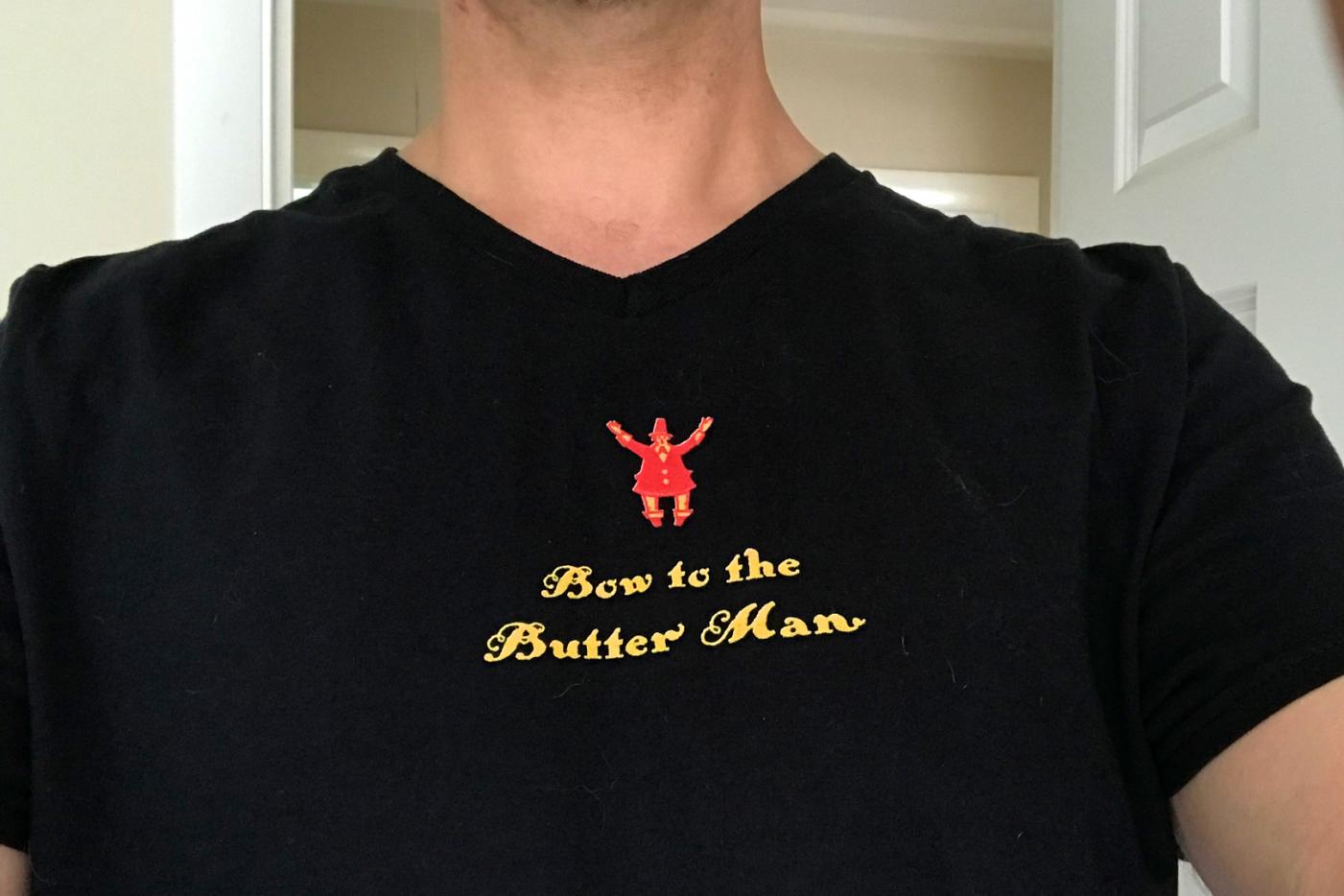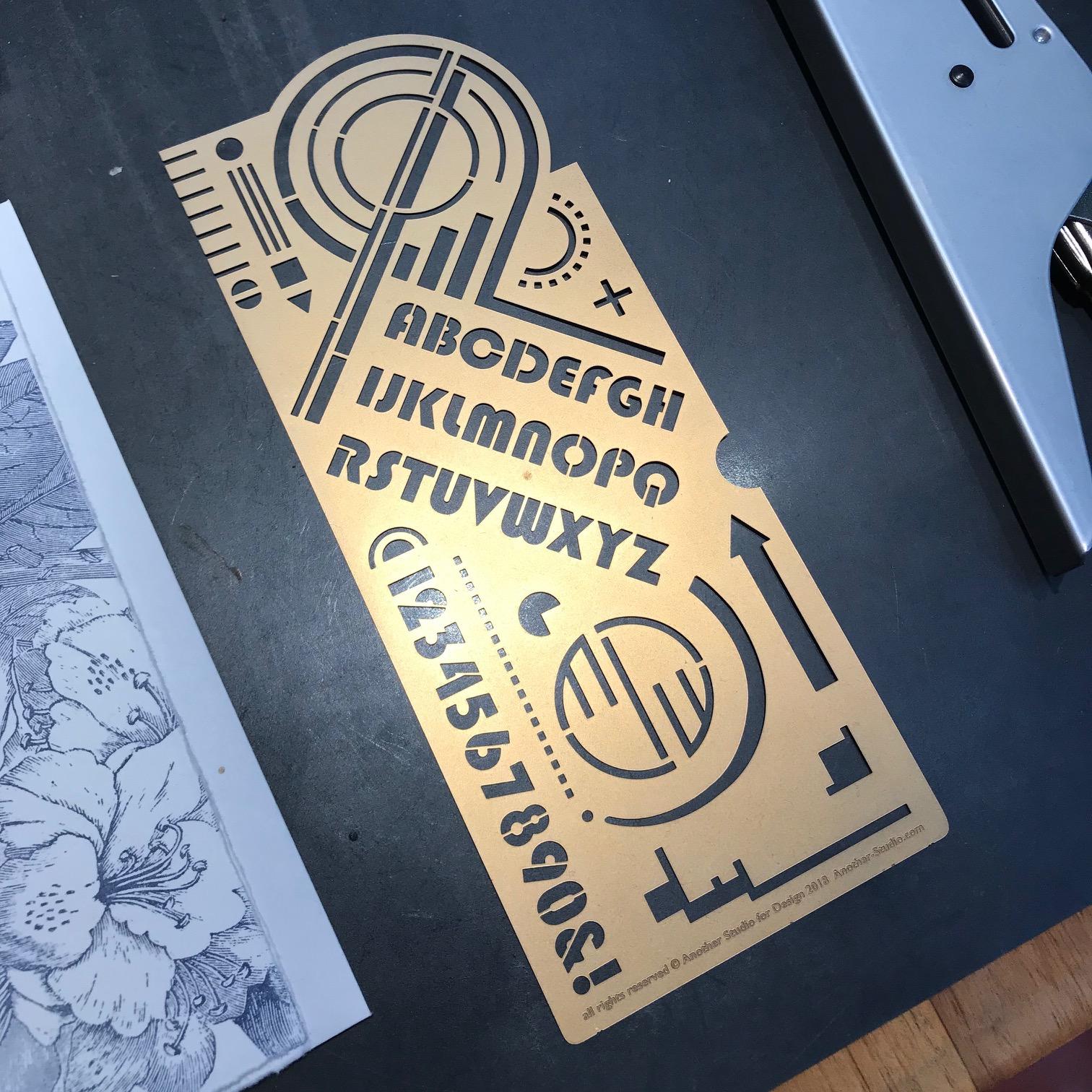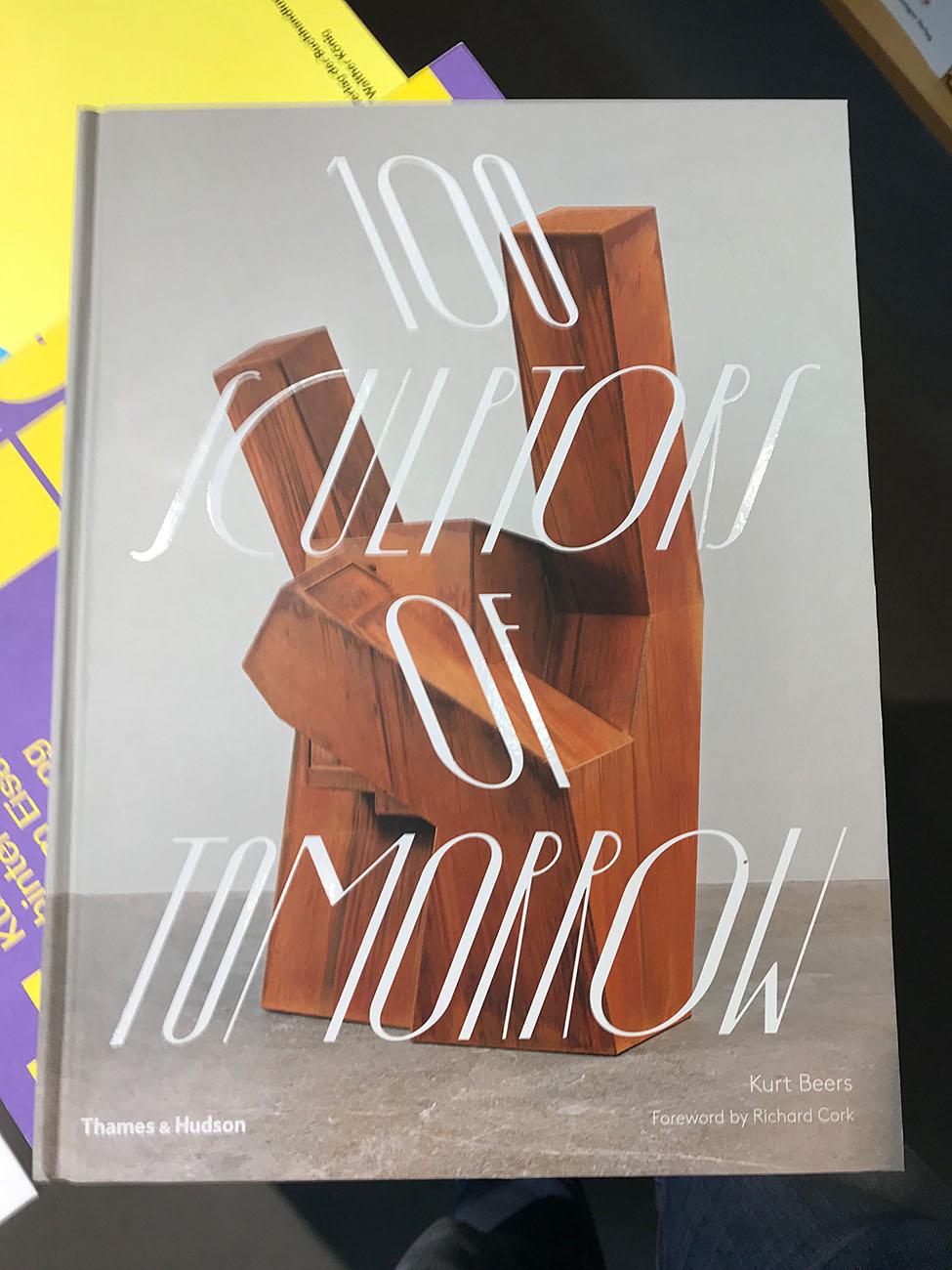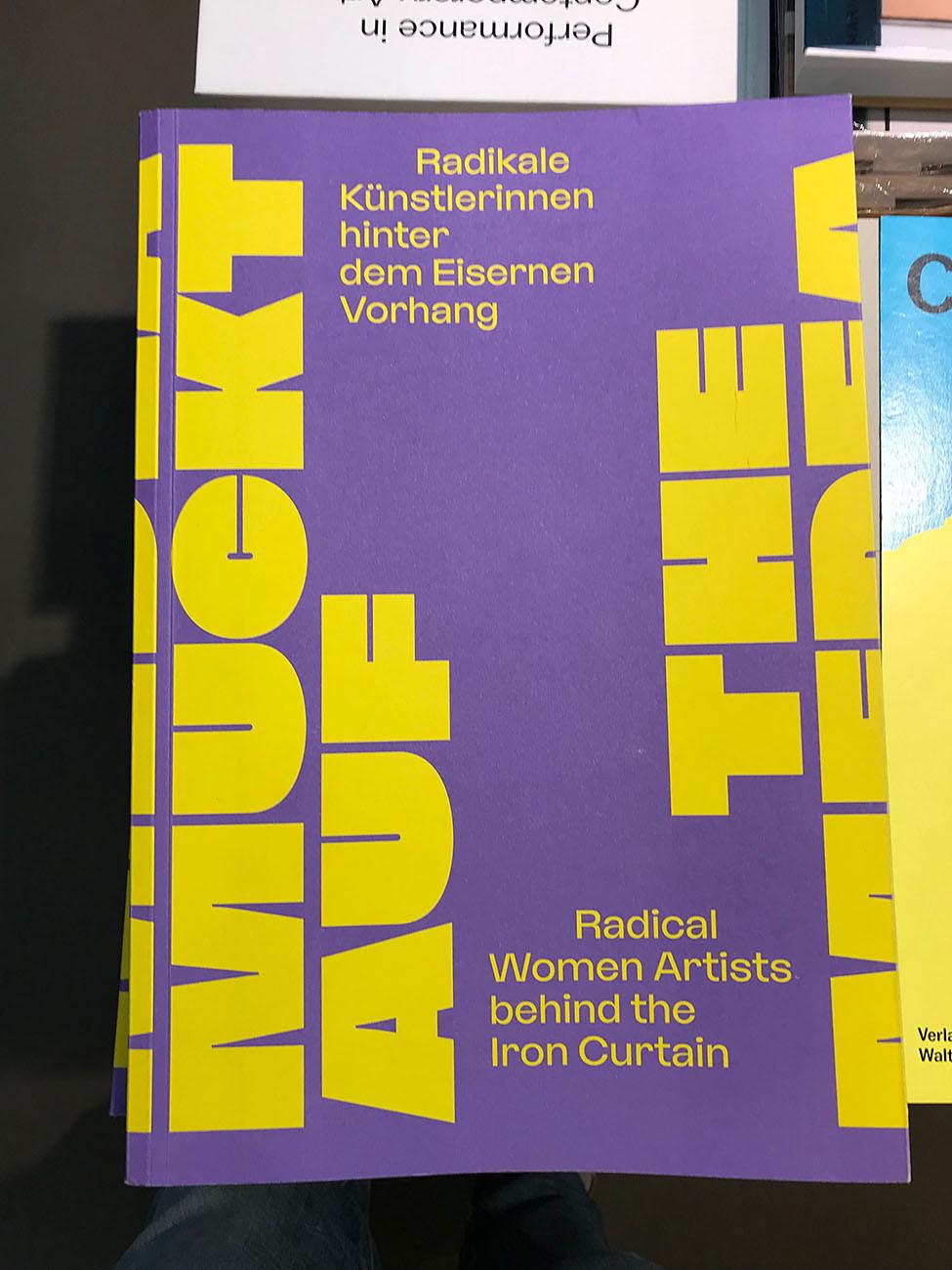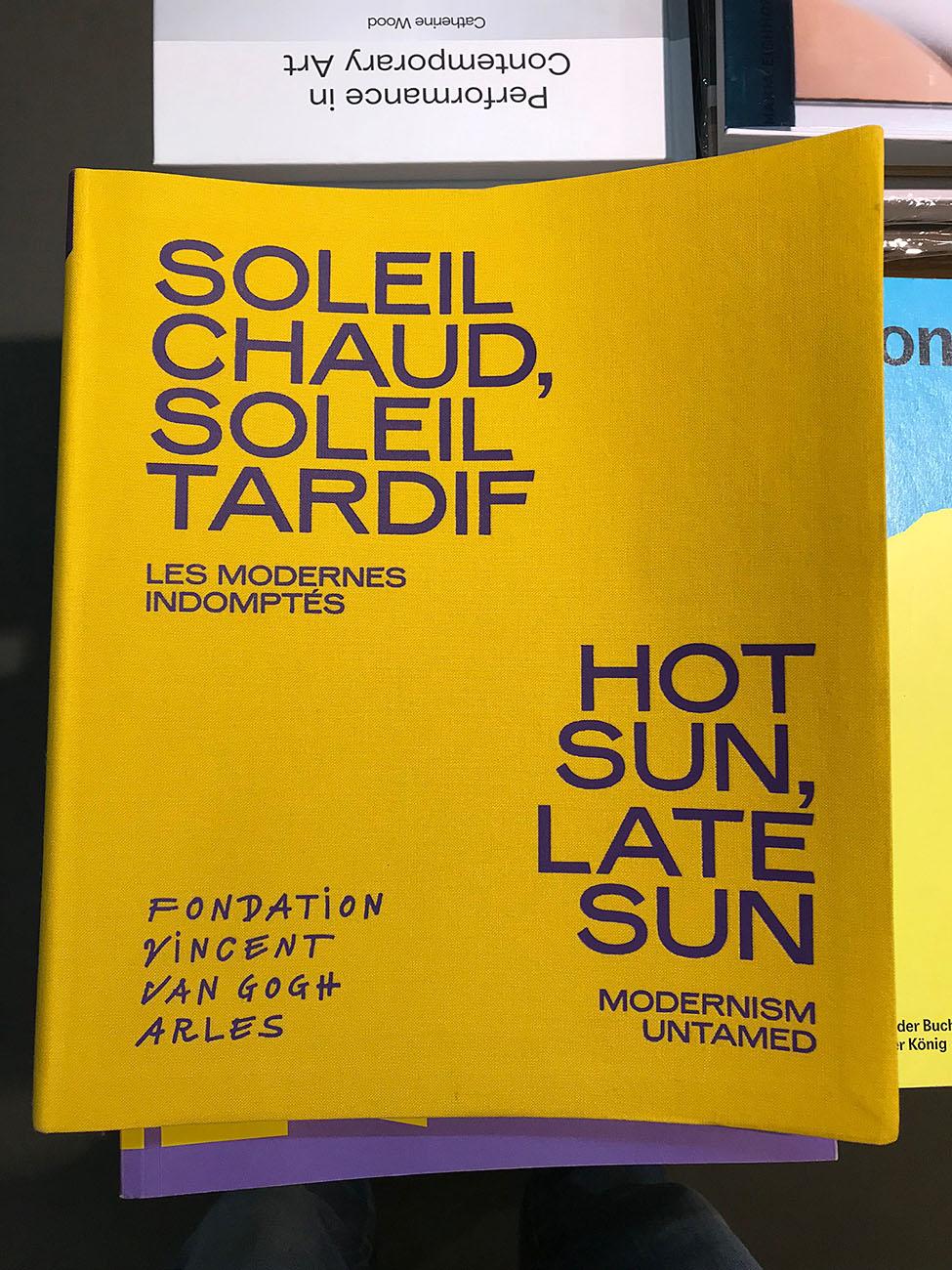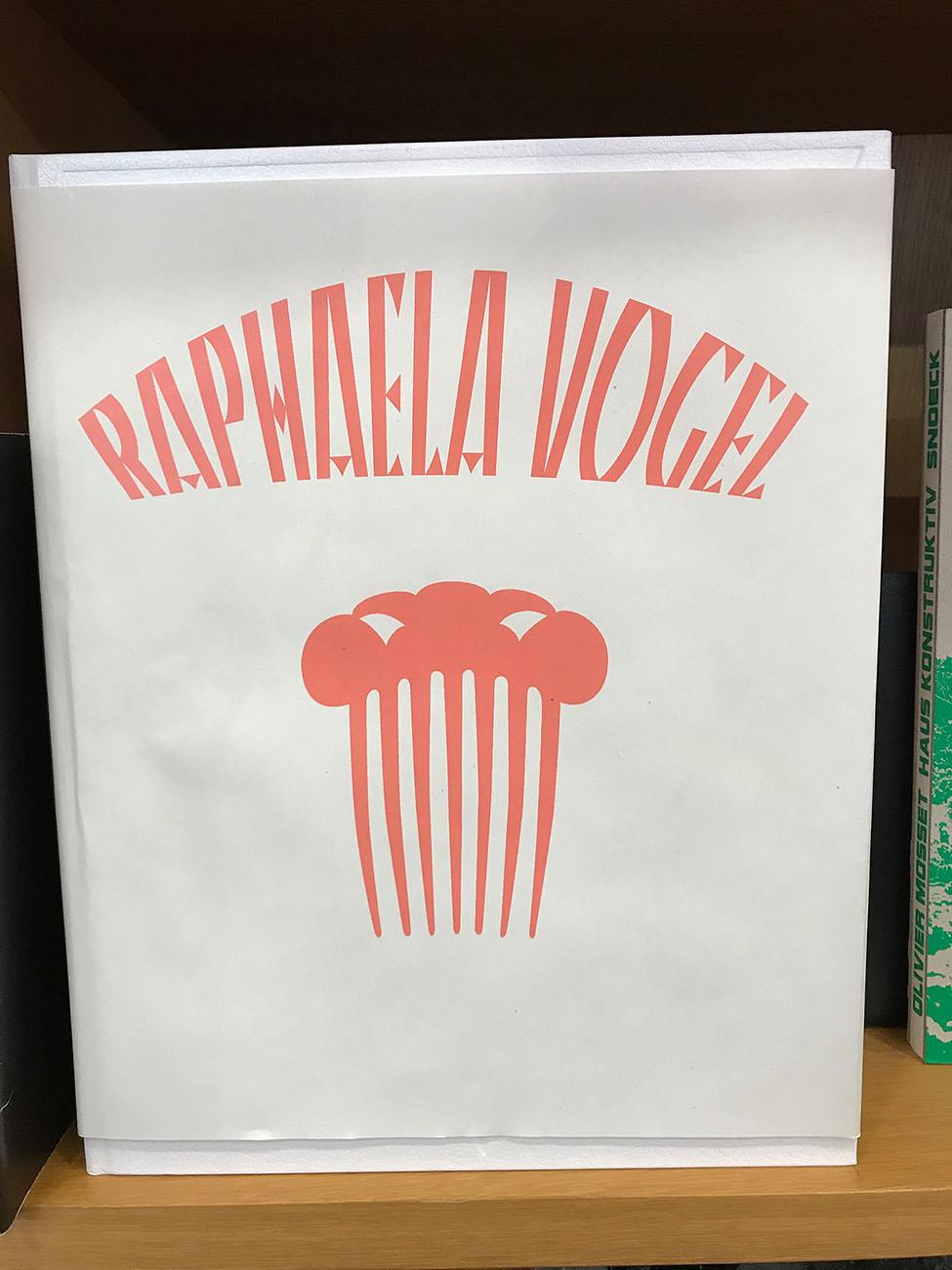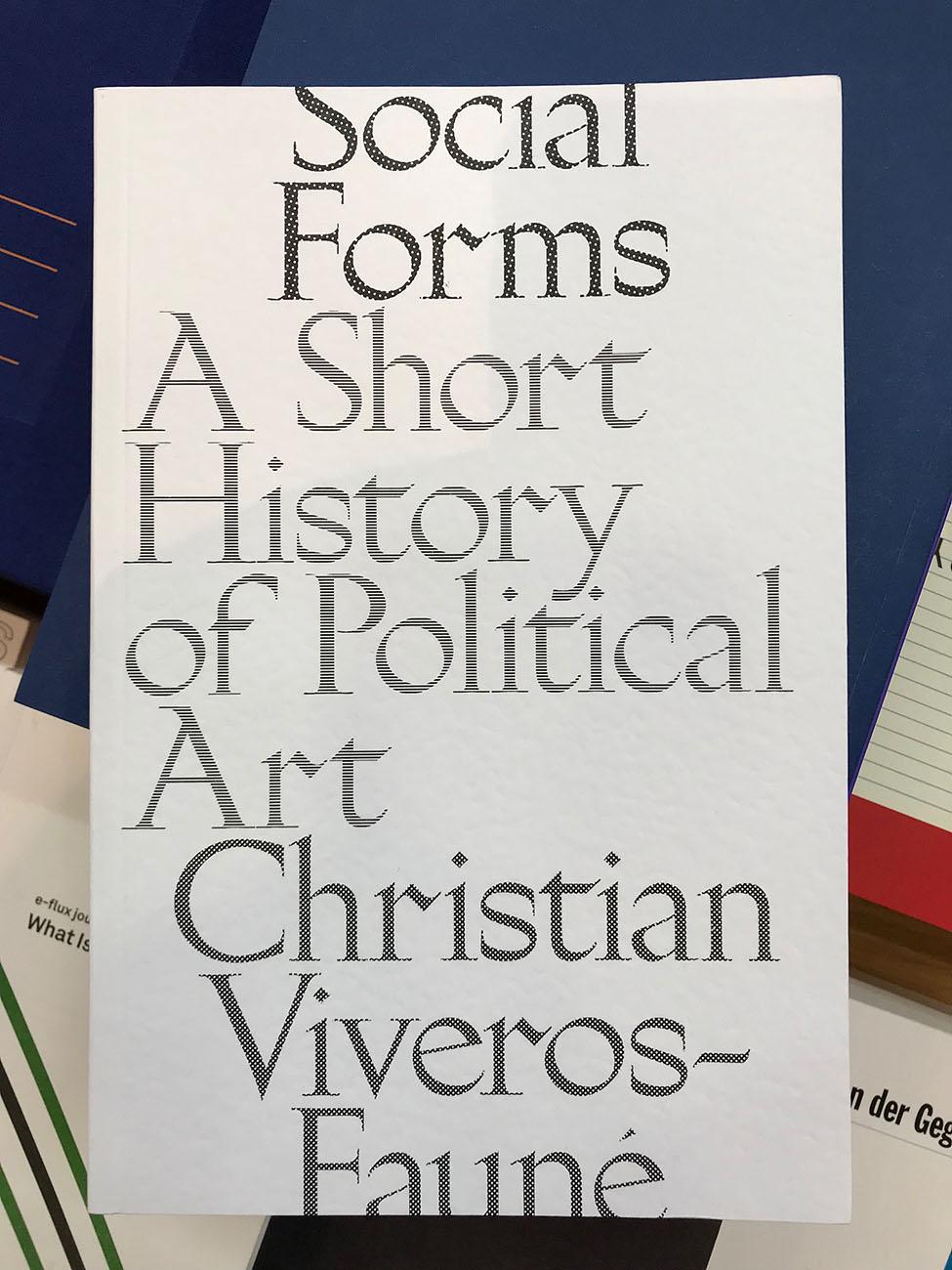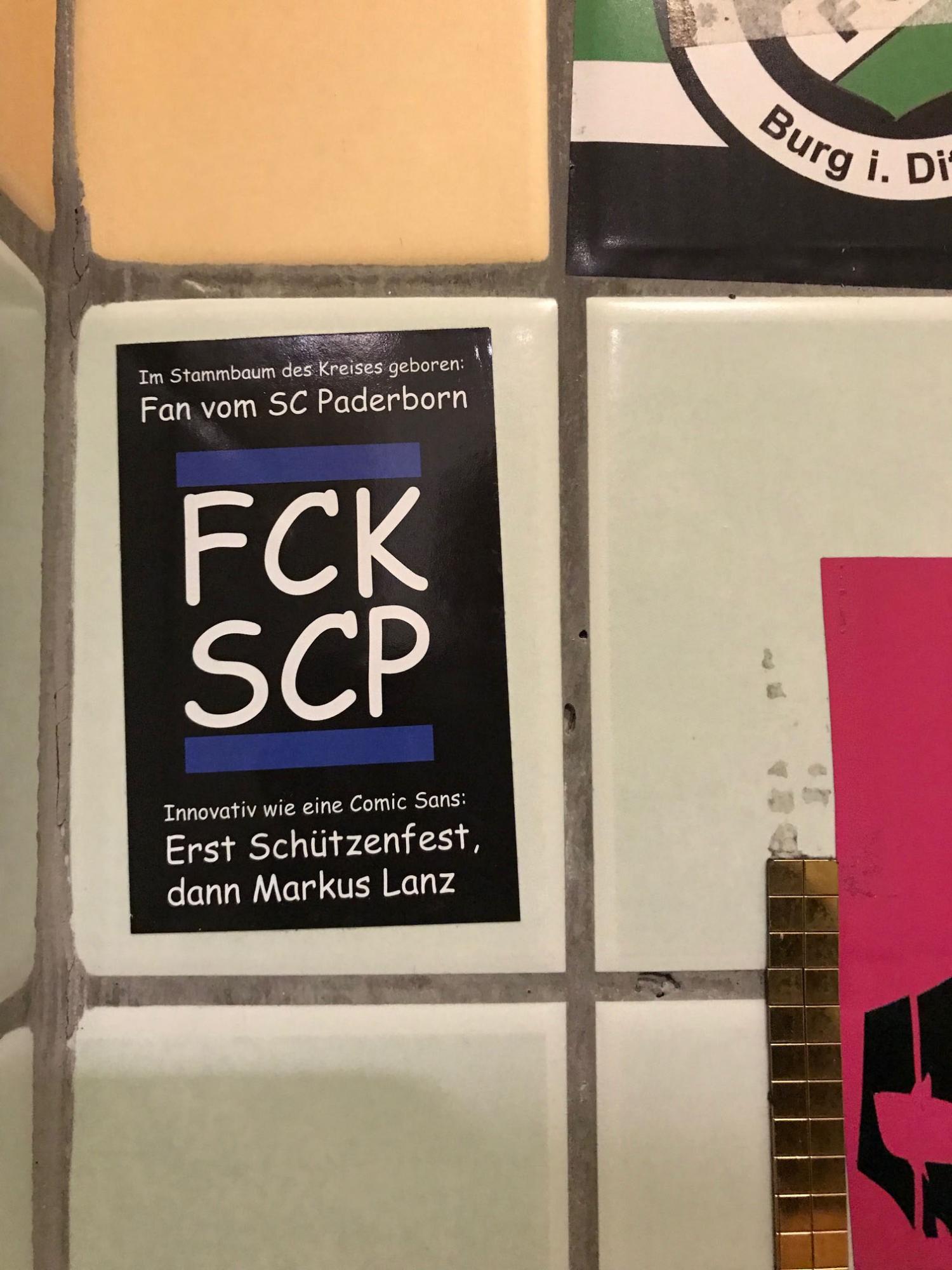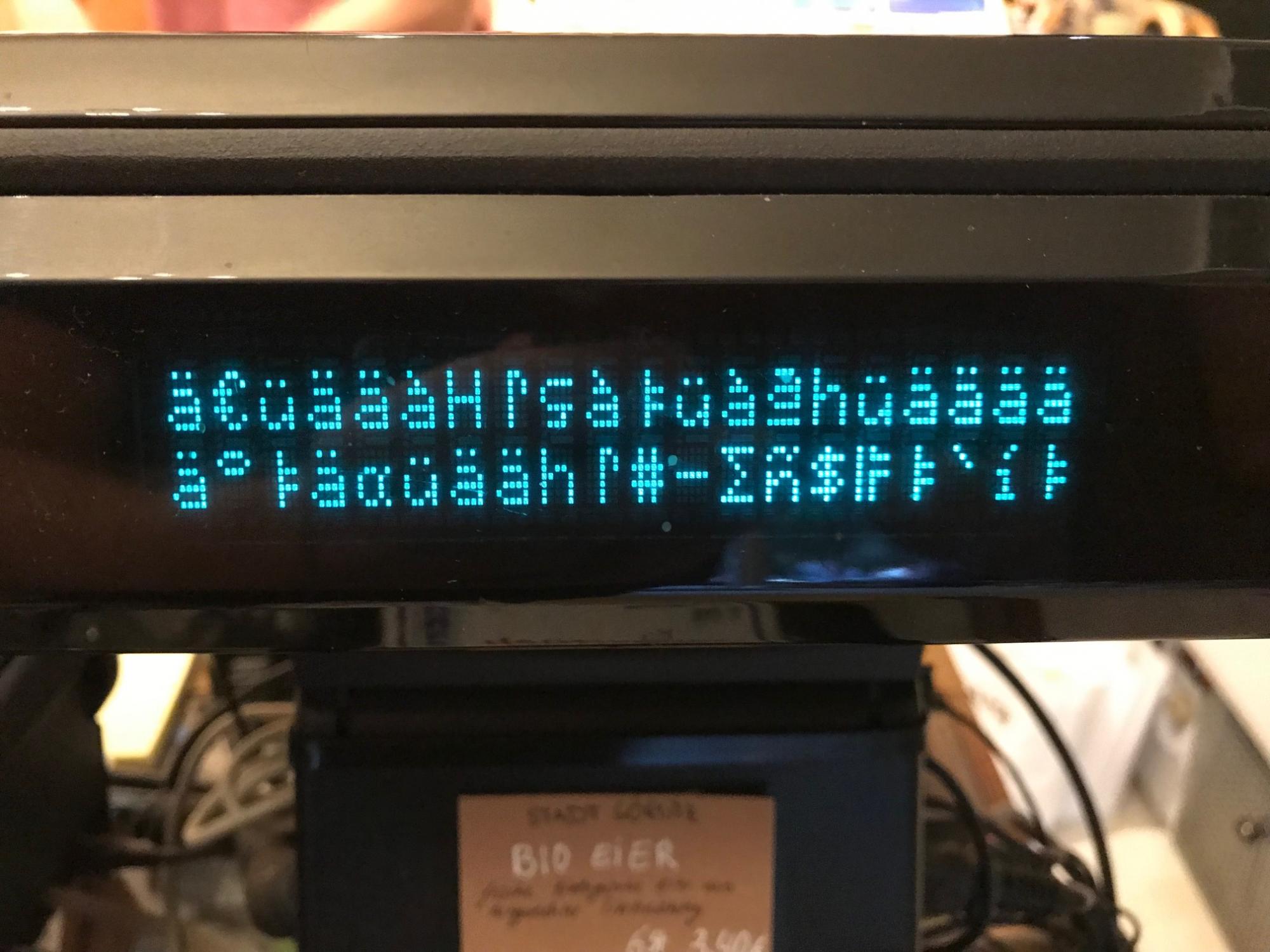
Ist das Buttermännchen in Originalgröße?
Wenn nicht würde ich sagen, dass könnte auch deutlich größer!
Könnte man für diese, wie auch für Christians kuschelige den Begriff Flexurschrift verwenden? Also für Schriften, die zwar vom Skelett her der Formensprache von Frakturschriften gehorchen, denen aber im Linienzug die harte Brechung fehlt, und eher Biegungen aufweisen.
Wobei ich mir ohne Kontext jetzt wohl nicht 100%ig sicher wäre, ob dort Nolde oder Noldc steht. :-?
Stimmt, das e hat hier viel vom, wie ich es gern nenne, Berliner c, also wie man es gerade im Berliner Raum bei Wandanschriften gerne genutzt hat, wo sich die c-Schablone nur durch einen später hinzugefügten Querstrich zum e ergänzt wurde. Beispiel hierzu meine "Berliner Wand"
Ich hab da noch ein historisches Fundstück:
Da hat der Setzer aber wirklich jeden vorhandenen Setzkasten eingesetzt, um mit der Vielseitigkeit des Kunden mithalten zu können. Fast schon ein Schriftmusterbuch auf einer Anzeige :-)
Da habe ich auch gestutzt, aber  damals Anfang des 20. Jahrhundert gab es eben neben Benzin und Ethanol (Spiritus) einige weitere exotische Treibstoff Mixturen aus Benzol (z.B. Aral als Marke des Benzol-Verbands aus Steinkohlenteer), Toluol, Aceton, Naphta, Petroleum unter unterschiedlichen Marken in den Handel, so Autin, Ergin, Autokraft,  Autonaphta, Motonapha und sogar Waltran usw. Dran schnüffeln sollte man aber besser auch nicht...
Heißt der Ort tatsächlich Wolagst oder sollte das eigentlich Wolgast heißen?
Ja, das sollte Wolgast heißen. Die Chaussestraße ist unsere Hauptstraße vom landseitigen Ortseingang bis zum Platz der Jugend im Zentrum.
Irgendwie auch ein H …
Das »H« finde ich recht klassisch – lediglich der Übergang zum »u« ist etwas experimentell ...
Kürzlich im Museumsshop: